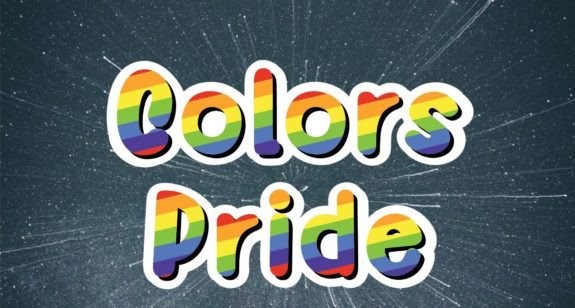
Colors Pride Font – أطلق العنان لإبداعك مع هذا الخط الفريد!
يتميز Colors Pride Font بتصميم عصري وجذاب يعكس التنوع والحيوية، مما يجعله مثاليًا للمشاريع الإبداعية التي تحتاج إلى لمسة فنية مميزة. سواء كنت تعمل على تصميم شعارات، بطاقات دعوة، محتوى وسائط اجتماعية، أو حتى مشاريع الطباعة، فإن هذا الخط يمنحك المرونة والتأثير البصري القوي الذي تحتاجه.
✔ تصميم أنيق وفريد يعكس ألوان الفخر والتنوع
✔ مناسب لمجموعة واسعة من الاستخدامات الإبداعية
✔ يدعم اللغات المتعددة لسهولة التخصيص
أضف لمسة إبداعية وجريئة إلى تصاميمك مع Colors Pride Font – حيث تلتقي الحروف بالفن! ????✨